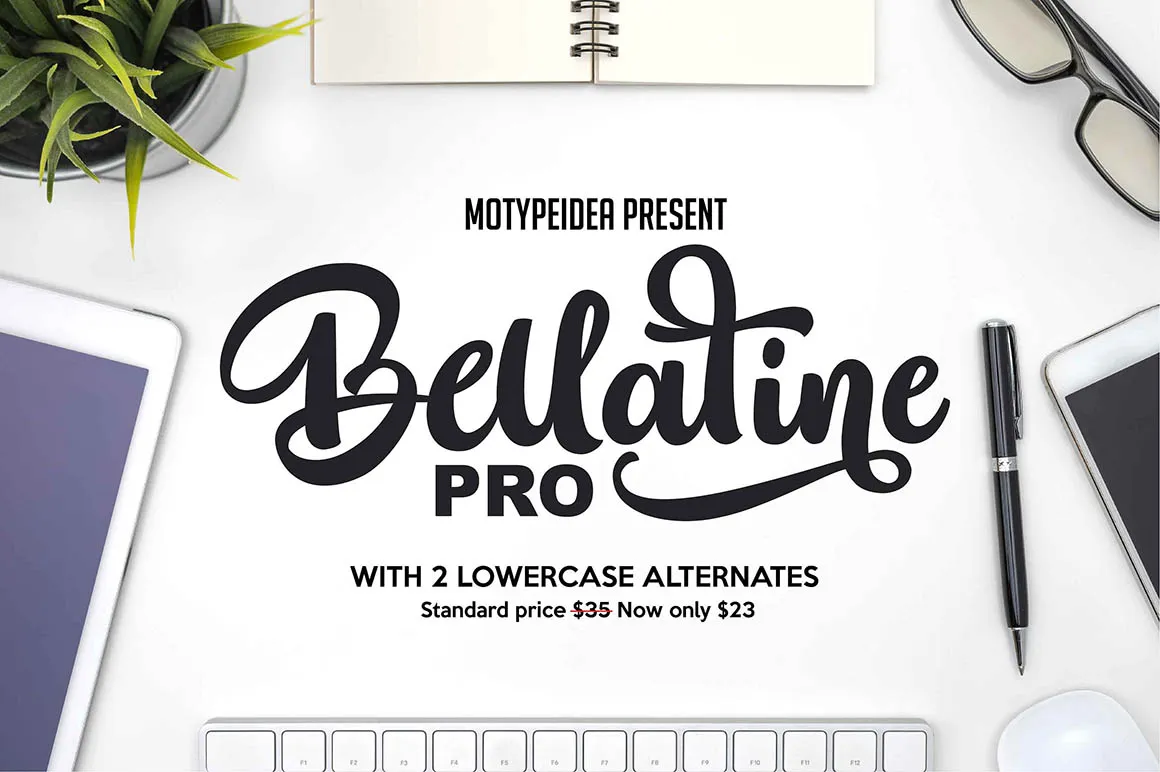
Bellatine Pro Script Font – Fonte Grátis
Bellatine Pro Script Font
Descubra uma nova fonte premium chamada Bellatine Pro Script Font, ideal para projetos digitais inovadores. Desenvolvida pelo designer Hamilton, esta fonte é perfeita tanto para adicionar um toque de elegância a cartões de convite nupculares quanto para tornar sua blogueira ainda mais única. Ideal não apenas para personalizar suas peças de escritório e produtos estilizados, como também para enriquecer capas de livros e até mesmo logotipos e molduras para sua casa. Em suma, Bellatine Pro Script é uma fonte criada especialmente para aqueles que buscam um equilíbrio entre elegância e personalidade em seus projetos digitais.